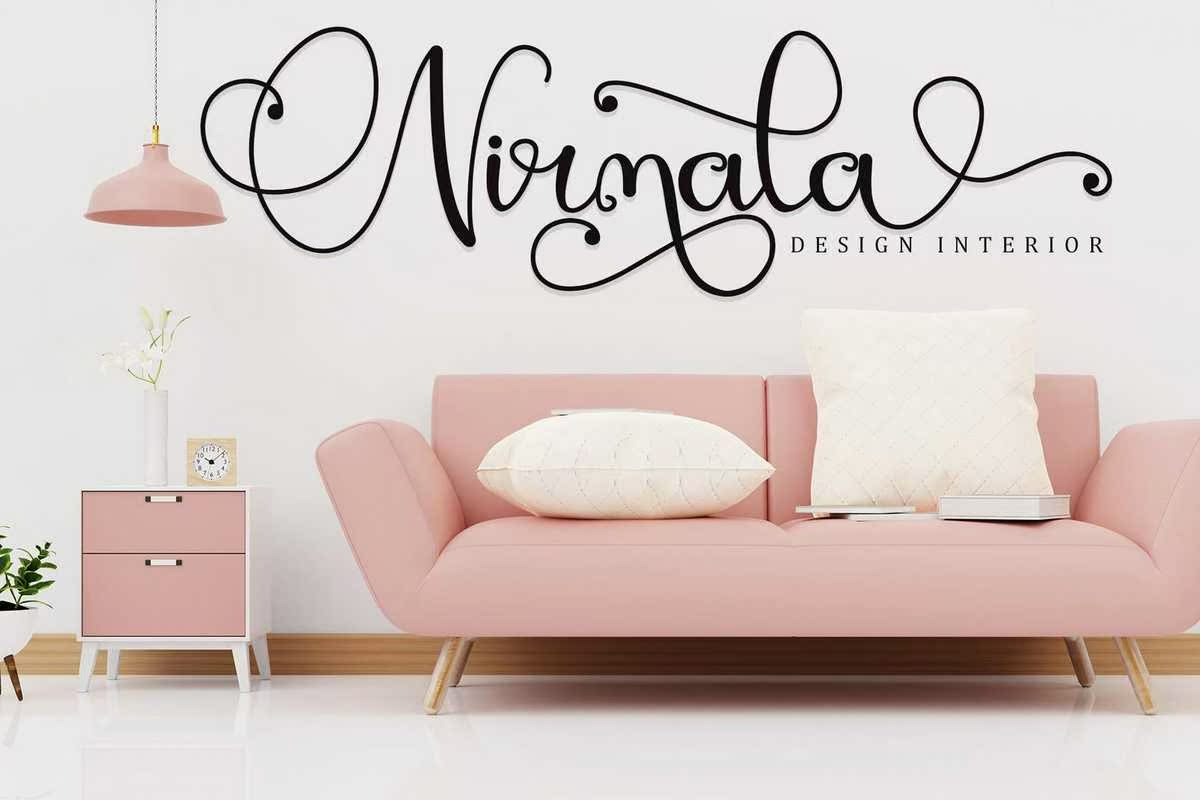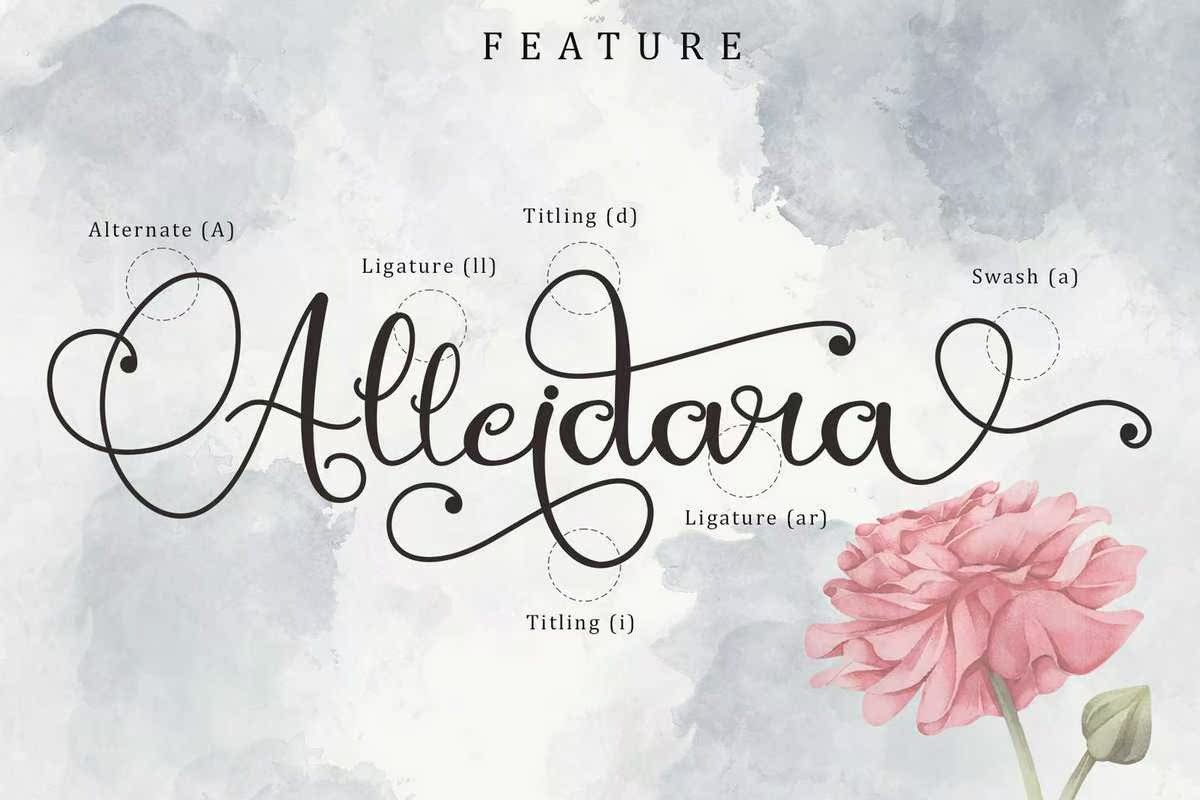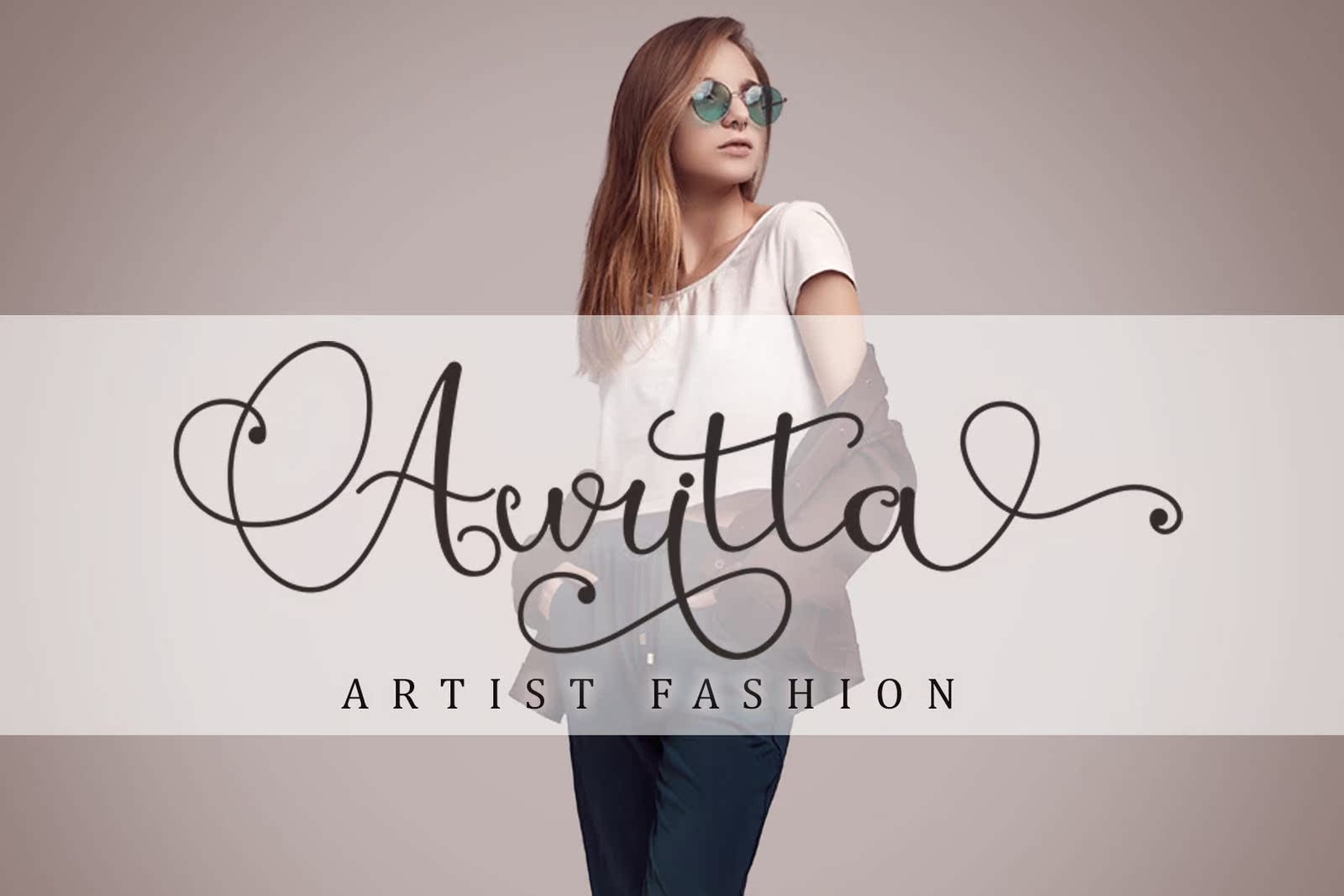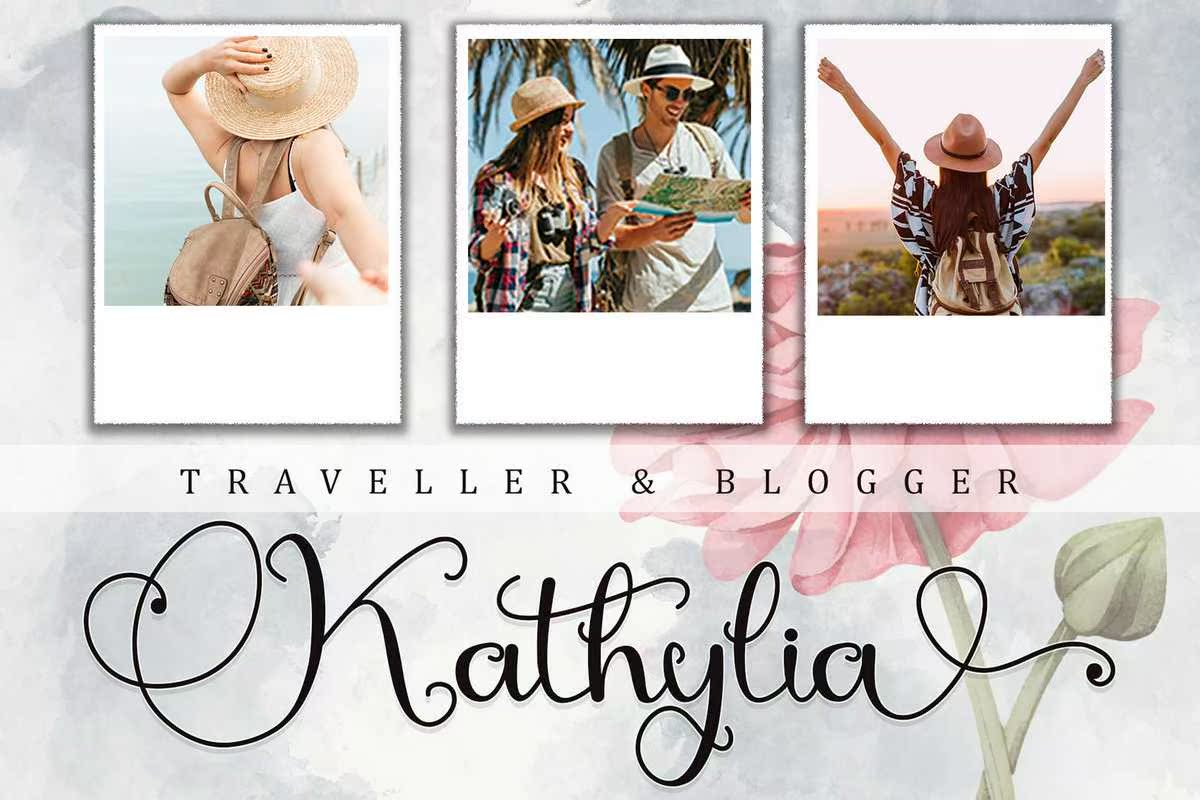
Miranda是一款现代书写字体。这款字体可以让您的书写和品牌更加优雅美丽。Miranda非常适合于独特的品牌、照片覆盖、水印、贺卡、海报、名片、请柬、婚礼、摄影、时尚、服装、信件、文具等。a-z,备选字体(A-Z)(A-Z)和连字包括,您可以使用您的徽标或手写字体、手写字体。Miranday现代和手写字体。这种字体可以使您的书写和品牌优雅或美观。Miranday适用于独特品牌、照片覆盖、水印、贺卡、海报、名片、请柬、婚礼、摄影、时尚、服装、信件、,文具等。一系列的水洗(a-z)、替代品(a-z)(a-z)和连字都包括在内,这样你就可以使用你的标识或字迹、手写本。